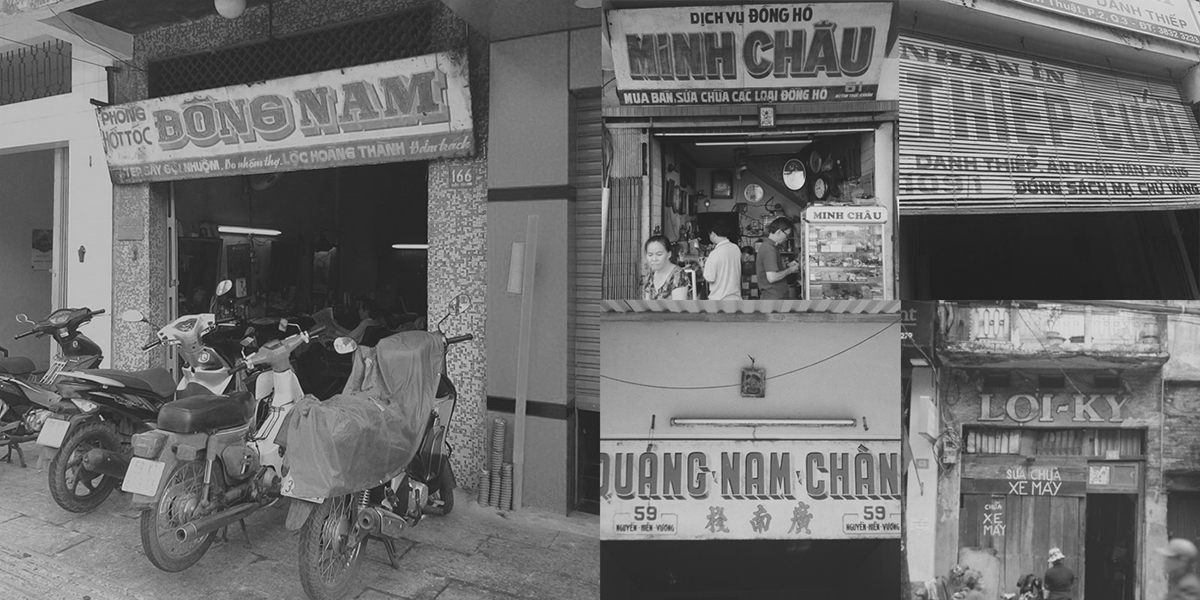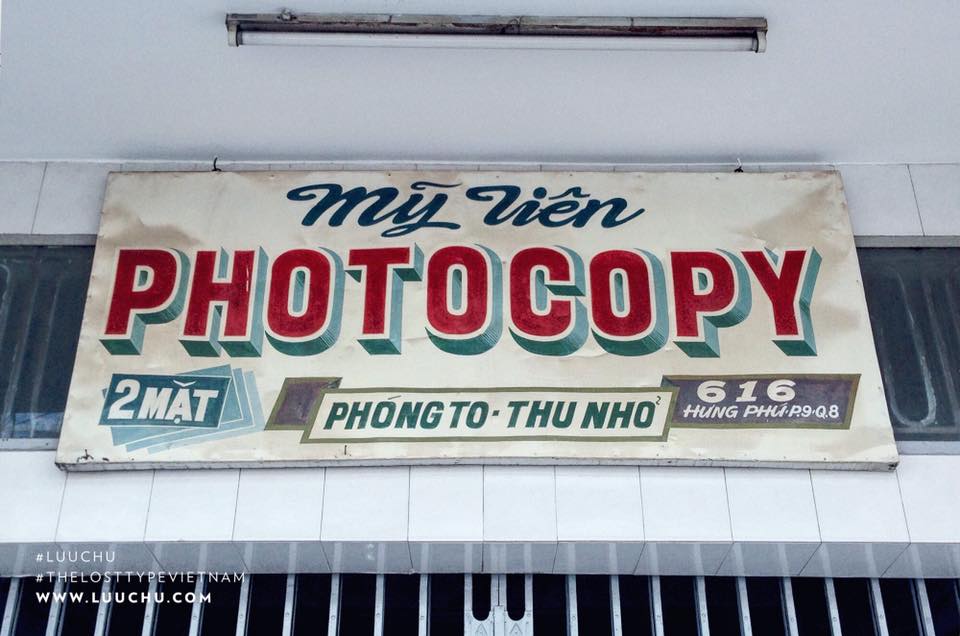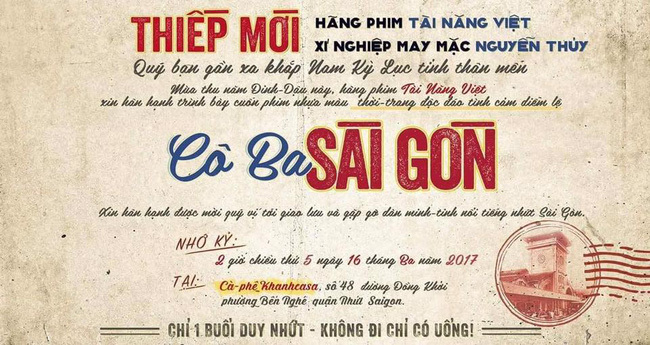
Font Chữ Sài Gòn Xưa
Font chữ được sử dụng từ bộ phim cô ba sài gòn đã tạo nên cảm hứng phong cách hoài niệm những năm 50 60 cực độc đáo và ấn tượng.
Font chữ sài gòn xưa. Font chữ classique saigon được sử dụng từ bộ phim đình đám cô ba sài gòn đã trở thành hiện tượng và khơi gợi nguồn cảm hứng cho những người thích hoài niệm đặc biệt là yêu mến kiểu chữ mà các biển hiệu sài gòn thập niên 50 60 thế kỷ trước. Font chữ cô ba sài gòn lấy nguồn cảm hứng từ những tấm pano áp phích biển hiệu của sài gòn những năm thập niên 50 60 thế kỷ trước. Font chữ được sử dụng từ bộ phim cô ba sài gòn đã tạo nên cảm hứng phong cách hoài niệm những năm 50 60 cực độc đáo và ấn tượng. Font chữ được sử dụng từ bộ phim cô ba sài gòn đã tạo nên cảm hứng phong cách hoài niệm những năm 50 60 cực độc đáo và ấn tượng.
Màu sắc hình ảnh phông chữ cách sử dụng từ ngữ trên poster đều thể hiện sự đầu tư công phu trong việc đưa văn hóa sài gòn đến gần với công chúng.